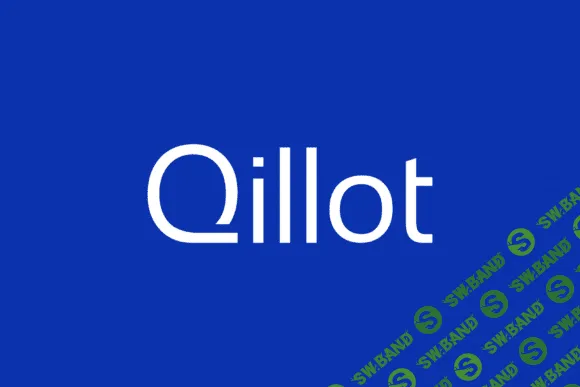
Название: Qillot Font
Qillot - это минимальный и аккуратный шрифт без засечек.
Его легко подогнать под невероятно большой набор проектов, так что добавьте его к вашим творческим идеям и заметьте, как он выделяет их!